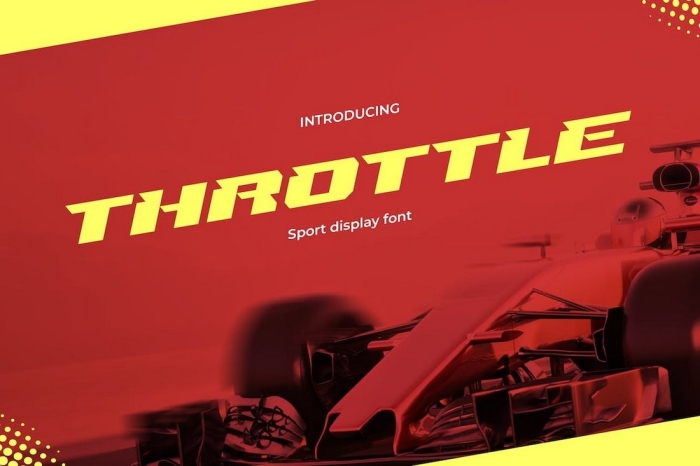
Avete in mente un nuovo progetto che riguarda il mondo delle corse di auto o delle cose delle moto oppure che è stata commissionata la nuova lavorazione dedicata al mondo dei motori?
Ecco a voi 20 e oltre fonts creati proprio per essere utilizzati all’interno di progetti che devono esprimere al massimo la velocità ed il movimento con tutta la passione che ruota attorno ai motori
Scorreteli tutti alla ricerca di quello che mi piace di più è che diventa più interessante per il nostro nuovo lavoro o idea